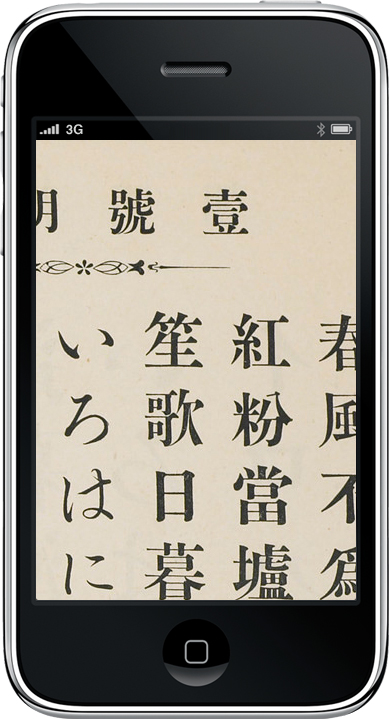
「秀英体見本帖」をAppStoreで無料配布開始 | DNP 大日本印刷株式会社
DNPとDNPデジタルコムは、iPhoneで電子書籍を閲覧するビューアを開発し、4/15よりAppStoreにて当ビューアを使用した電子書籍「秀英体見本帖」の無料配布を開始しました。
秀英体見本帖は、DNPの前身である秀英舎が、大正3年に発行した活版印刷の見本帖を再構成した内容です。およそ100年前の見本帖ですが、いま平成の大改刻でデジタルフォントにしている最中の初号明朝や、モリサワにライセンスした書体でもおなじみ、三号&五号明朝なども収録されています。
それもそのはず、秀英舎では明治30年ごろからこつこつと書体の改刻を進め、いわゆる「秀英型」という独自のスタイルを完成させていますが、大正3年の見本帖には、その完成期の秀英体がいいタイミングで収録されているんです。
見所はコンテンツだけではありません。閲覧用のビューアは、DNPが自社で開発したものです。
このビューアは、紙の本を、レイアウトそのままに電子書籍化する際に使っていただこうと開発しました。ですので、ページの拡大・縮小機能が備わっています。雑誌や写真集などにおすすめのビューアです。
とってもシンプルな機能のビューアですが、ページの移動のスムーズさに工夫をこらしました。電子書籍ですから、あれこれ機能を詰め込んで動作が重くなってしまっては元も子もありません。初めて使った方でもわかりやすく操作でき、気持ちよくページがめくれる、というユーザ本位の設計が自慢です。